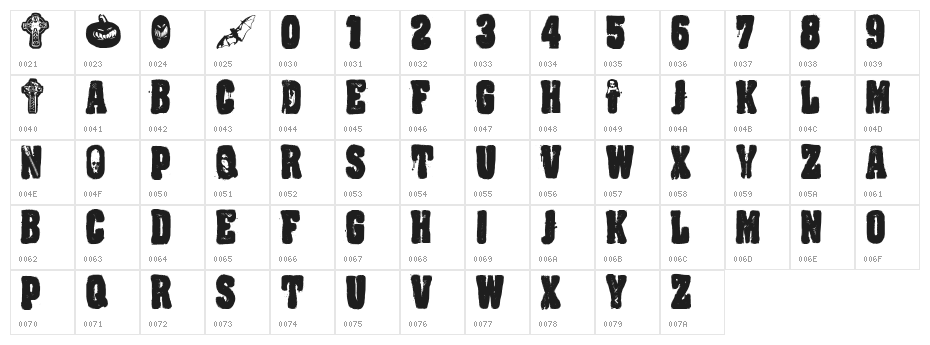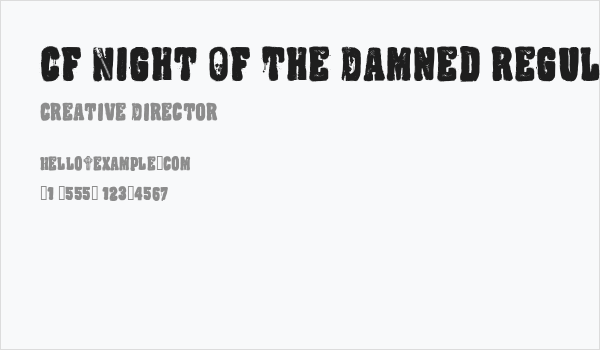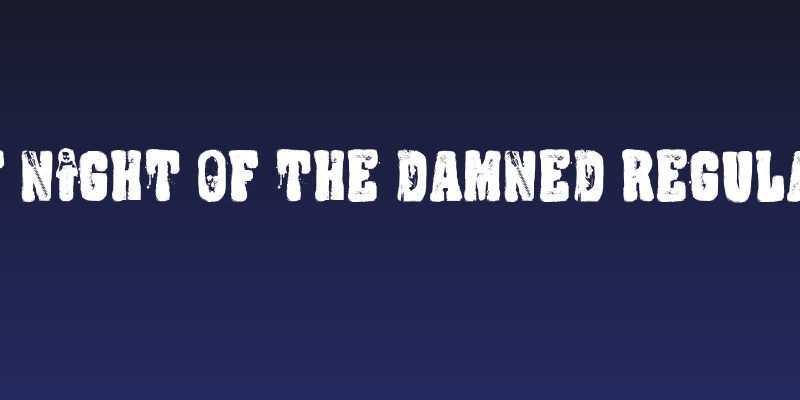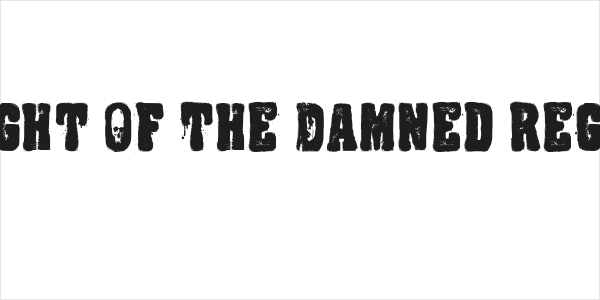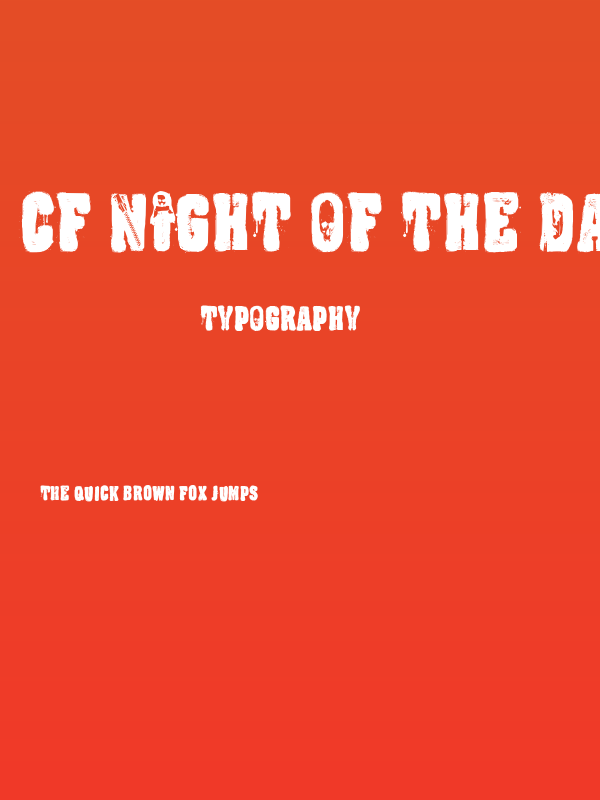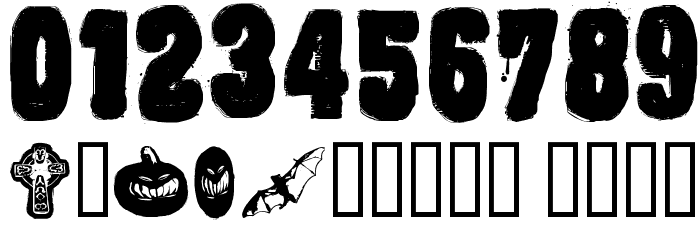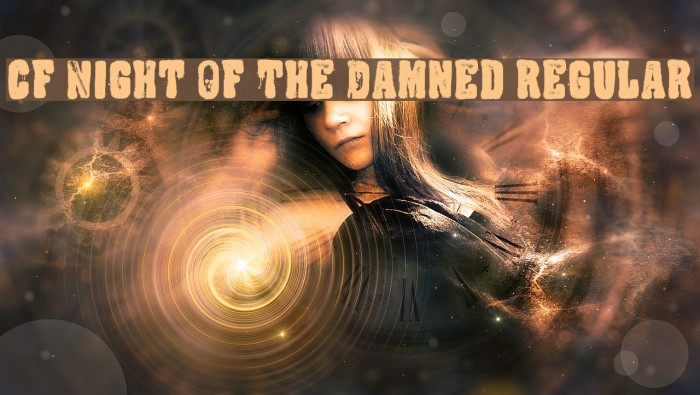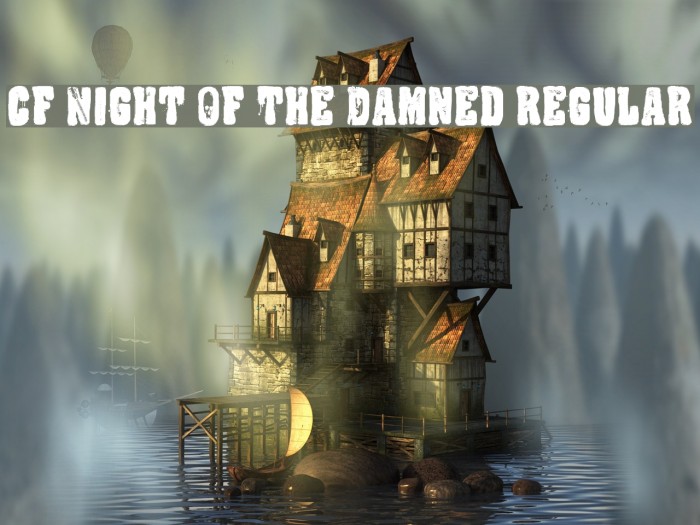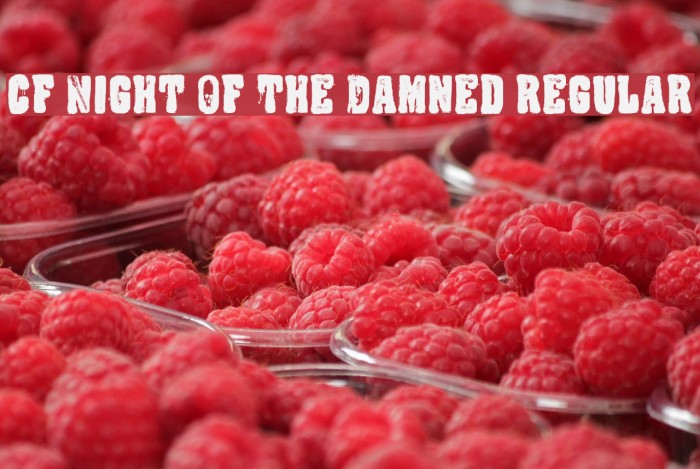
CF Night Of The Damned Regular Font
| Projets proposés | Perfect for Halloween posters, horror movie titles, themed party invitations, and haunted house signage. |